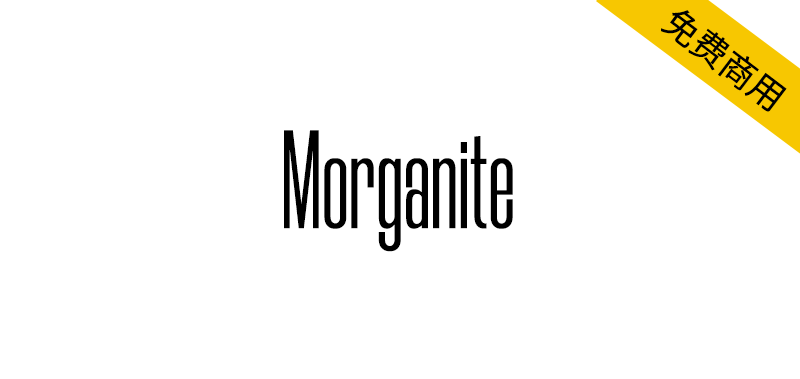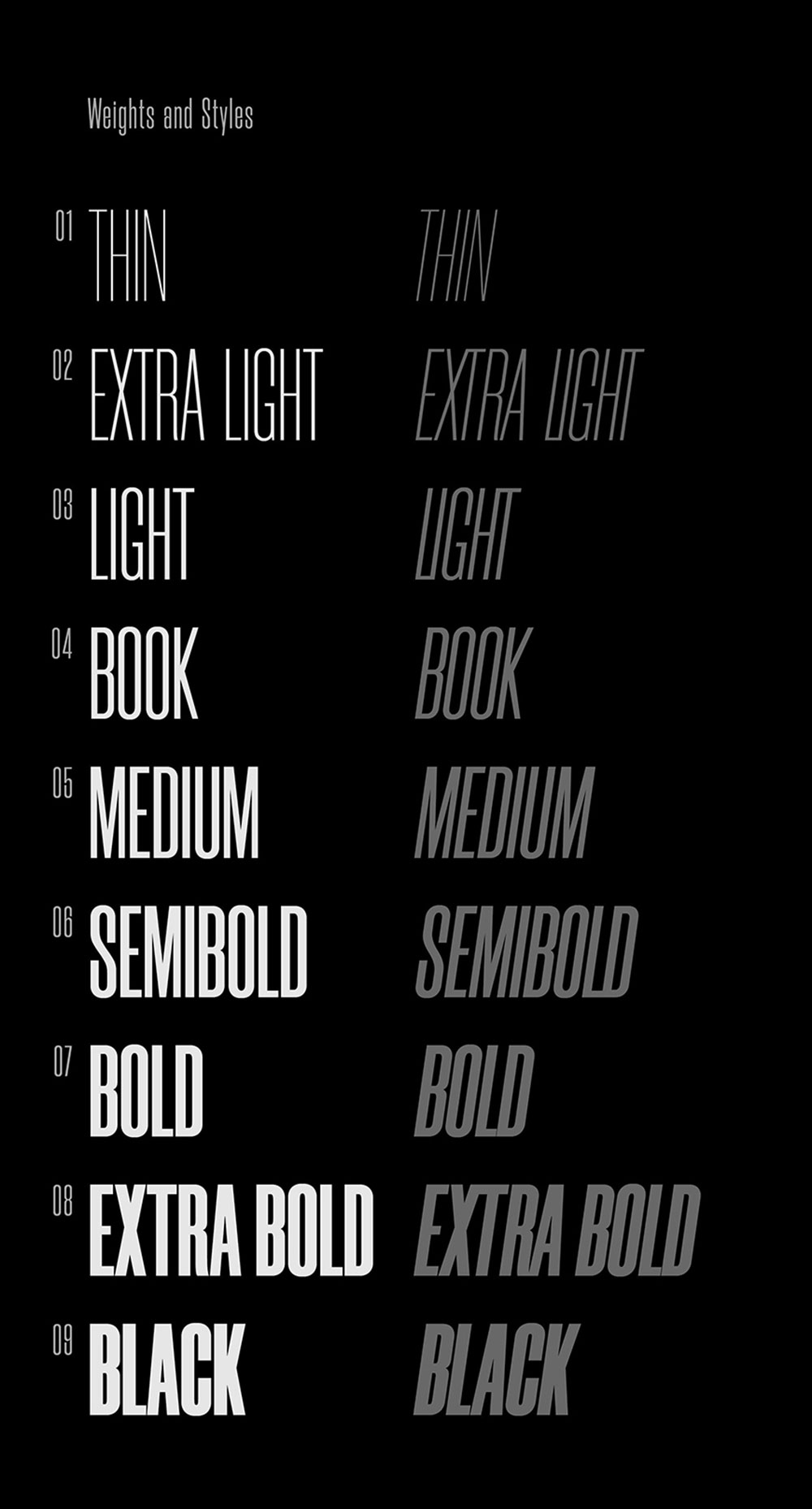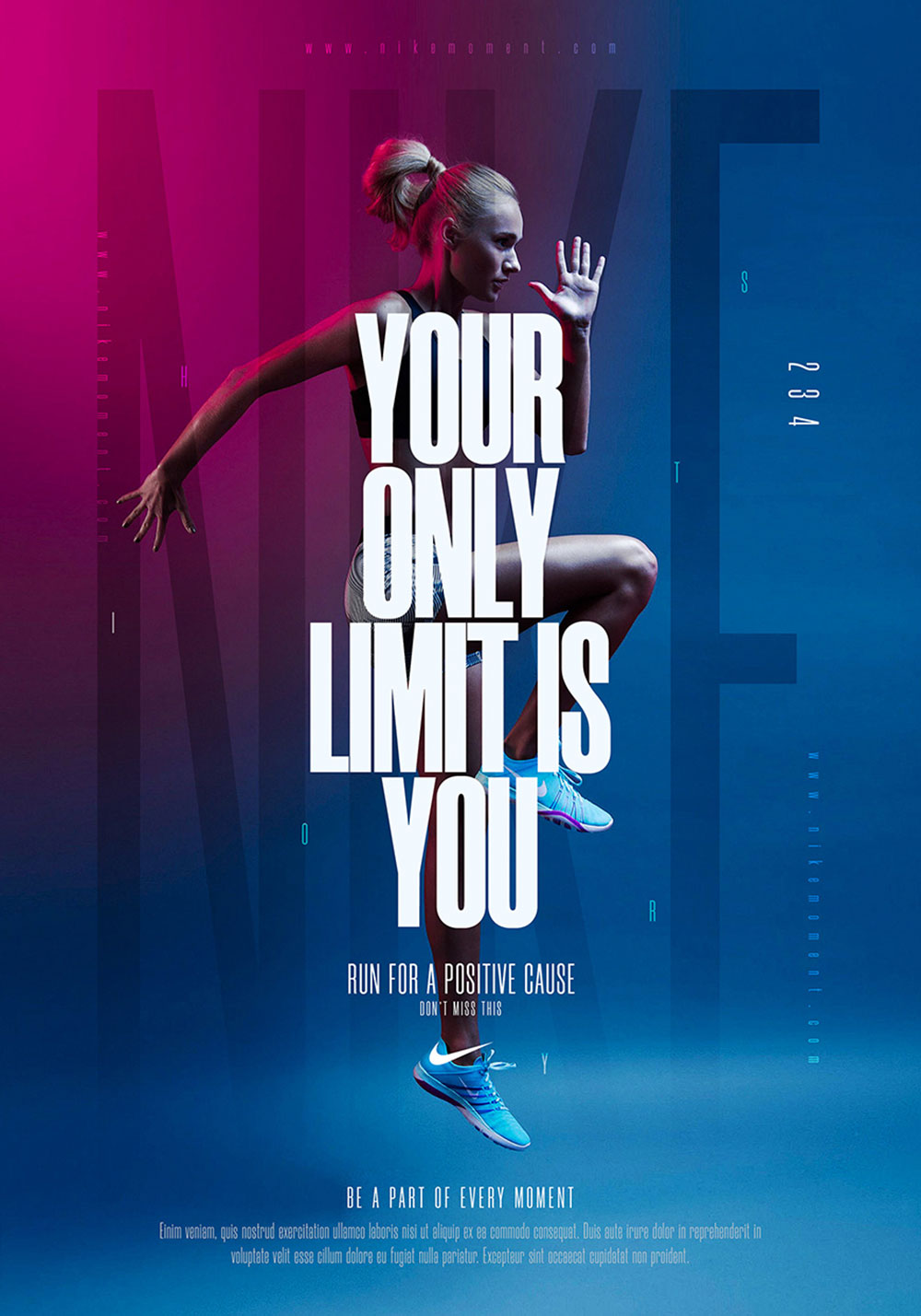
【Morganite】非常适合用在时尚、高端类型的海报设计作品
Morganite字体由印度新德里的设计师Rajesh Rajput所设计,可以免费用于个人和商业项目。但是未经书面许可,不得修改字体文件,用于二次发售,这也是对设计师的尊重,字体包括18种风格,从细到粗,还有倾斜体,字体风格非常优美,非常适合用在时尚、高端类型的海报设计作品。
Morganite字体包括18种风格,从细到粗,还有倾斜体,字体风格非常优美,非常适合用在时尚、高端类型的海报设计作品。
【Morganite】非常适合用在时尚、高端类型的海报设计作品